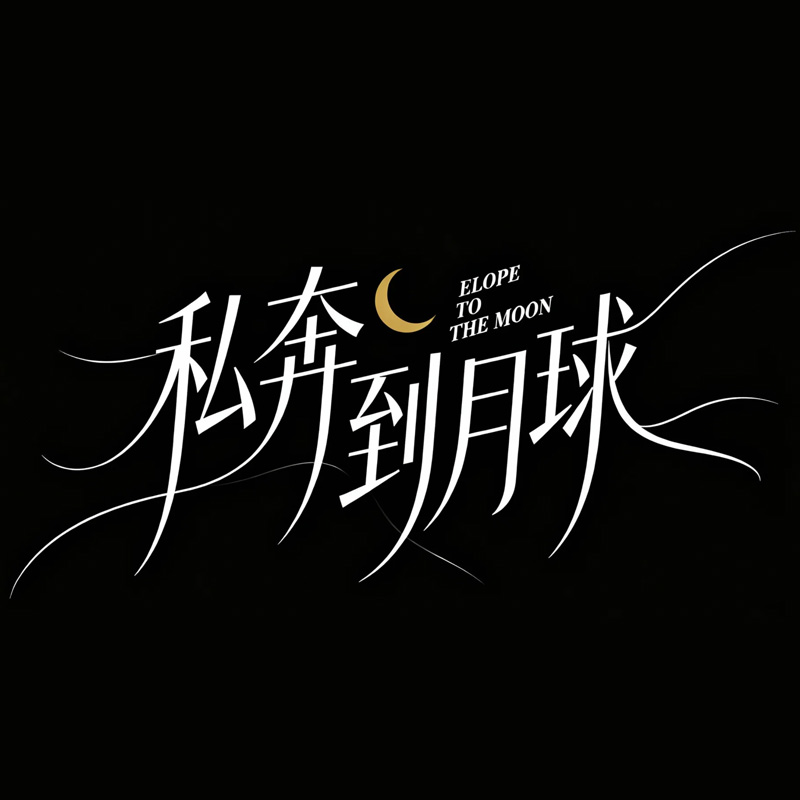
字体设计,商业级手写艺术标题字作品,大师级排版,黑色背景白色字,中央是非常纤细夸张的手写体的中文标题“私奔到月球”,字体笔非常触纤细利落,字形错落分布,笔触流畅而富有动感,带有诗意手写感,部分字体一些笔画被拉长,显得飘逸灵动,笔画很有特色,笔画线条带延伸感,字体线条灵动,带着一种漫不经心的文艺感, 在“奔到月球”的上方,有一个金色的新月(弯月)图标,在新月和中文标题的右上方,有一行倾斜放置的英文小字“ELOPE TO THE MOON”,字体是无衬线手写体,字母之间有一定的间距,